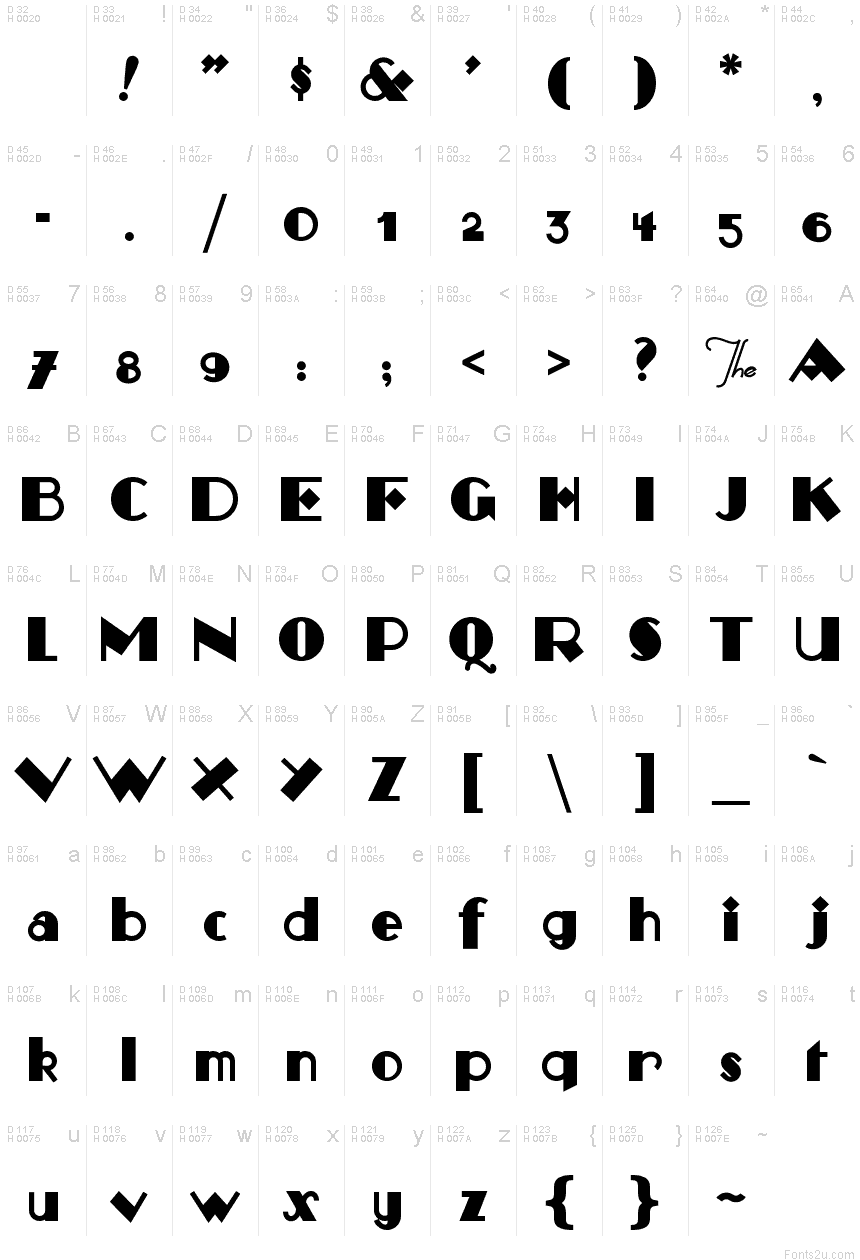
Monkey-Fingers autorstwa Nicka Curtisa to darmowy, retro krój typu display o ostrych, kanciastych cięciach i zaokrąglonych wewnętrznych łukach. Litery łączą w sobie blokową konstrukcję z miękkimi, kolistymi kształtami, nadając projektowi wrażenie ręcznego wycinania przy zachowaniu uporządkowanego rytmu.
Monkey-Fingers świetnie sprawdzi się w tytułach plakatów, logotypach, opakowaniach, okładkach albumów czy szyldach w stylu vintage, gdzie litery muszą mieć silną graficzną obecność. Ten darmowy font pasuje również do krótkich grafik w mediach społecznościowych i etykiet retro, zwłaszcza gdy chcesz, aby tekst niósł ze sobą cały design dzięki swoim kanciastym kształtom litery M i miękkim, okrągłym światłom wewnątrz liter.